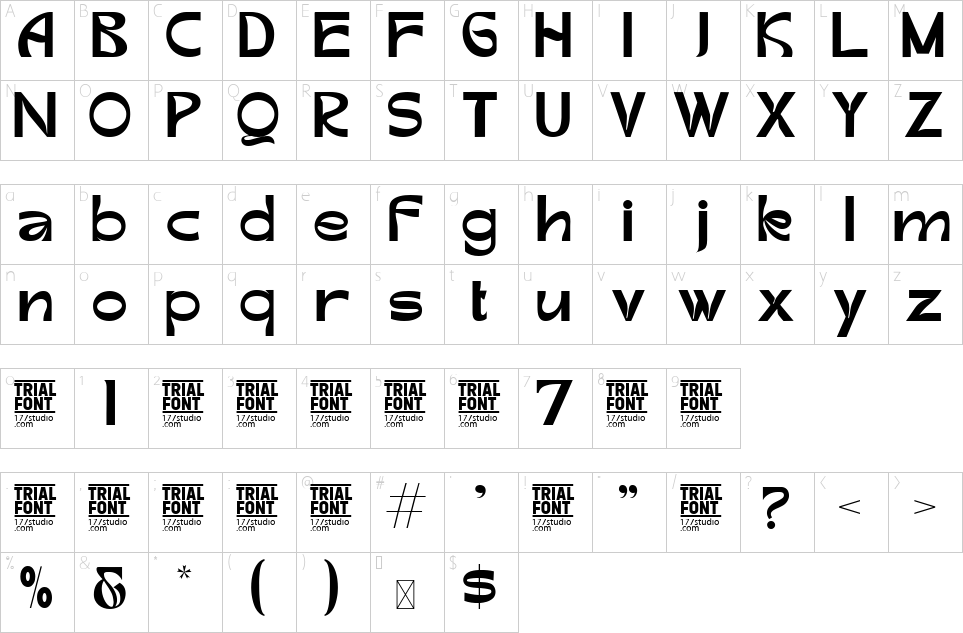
Aqui está uma descrição curta e envolvente em português para a página de download da font ‘Gares Font’: A Gares Font é uma elegante opção para quem busca fontes modernas e sofisticadas para projetos gráficos digitais. Desenvolvida pela 177studio.com, esta font oferece um conjunto completo de letras capazes de criar designs atraentes sem comprometer os requisitos estéticos ou legais. Com uma arquitetura limpa e um amplo espectro de caracteres, Gares atende às necessidades dos designers digitais que valorizam não apenas a funcionalidade, mas também o aspecto visual de suas criações. Estendendo-se para os projetos de desktops Windows e Mac, Gares Font é uma opção extremamente versátil. Para aqueles que buscam fontes gratuitas que possuam qualidade de design e se integrem facilmente a seu trabalho diário, esta font será um excelente investimento. Com um total de 1.130 downloads desde sua disponibilização, a Gares Font já conquistou o favor da comunidade de designers digitais no Brasil e em outros países. Compreendendo as necessidades dos profissionais de design modernos, 177studio.com oferece uma font que se alinha perfeitamente ao seu trabalho diário. A Gares Font não apenas atende a requisitos estéticos, mas também permite flexibilidade para criar designs personalizados e atraentes sem comprometer a qualidade do trabalho.